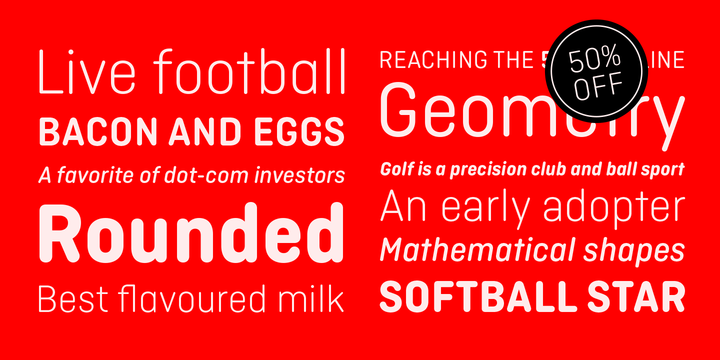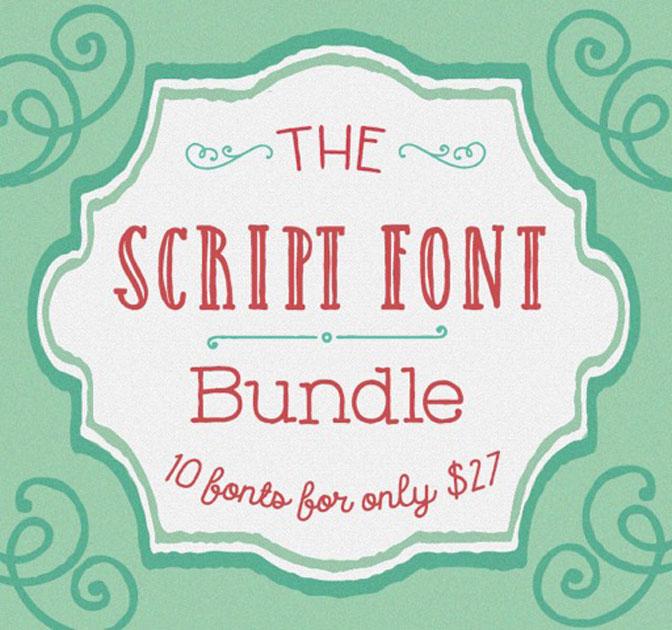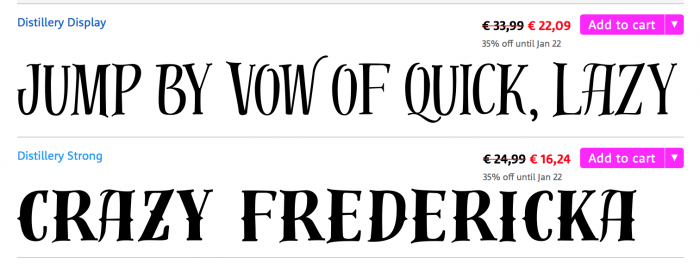
Aber im Ernst: Soll ich noch mal einen»echten« Text zum Vergleich setzen?
Na, Phantasielatein lese ich nun ja schon seit mehreren Jahren ... daran liegt's nicht. Denn auch den Echttext empfinde ich nicht angenehm im Auge. (Das liegt aber nicht an deinem bezaubernden Text – irgendwie sperrt sich die DINSlab meinem Lesefluss entgegen).
Leider fehlen bei mehrere dieser Schriften jegliche Form von Sprachunterstützung, und sind also nur für englisch geeignet. Trotzdem aber für die andere Schriften kein schlechter deal.
Das stimmt, bei Hipsteria und Graceful fehlt sogar das ß, was sie in unseren Breiten leider ziemlich unbrauchbar macht.
Dann mach einen auf kosmopolitischen Pan-DACHler, der generell nur Strasse schreibt. Es soll ja sogar eigentlich gar nicht schweizerische Firmen geben, die derartige Praktiken pflegen. :hammer:  Aber im Ernst, das hier und da fehlende ß hat mich auch gestört.
Dabei haben all diese Fonts das in verbundenen Schreibschriften ziemlich unnütze Ð (Groß-ð)! Da haben wir’s mal wieder: der halben Million Isländischschreibern wird jeder obskure Wunsch erfüllt, aber 90 Millionen Ösi-Deutschländer werden diskriminiert! Wenn das mal kein Fall für PEGI[selbstzensur! :tutor:]
Aber jetzt wirklich im Ernst: die Schriften bieten auch positive Überraschungen. So haben einige sehr schön subtile Diakritika (so wie Handschreiber das oft machen), also nicht so übertrieben auf Unterscheidbarkeit getrimmt wie in zu vielen Fonts. :biglove:
Gerade bei MyFonts entdeckt: Café Brazil von Sofia Mohr
Café Brasil is a font designed to represent coffee, especially for use in packaging, brand titles, logos and menus. Based on the shape of a coffee bean, Café Brasil has delicate details and ligatures that represent the liquid, foam and steam of a good cup of coffee. In March 2014, Café Brasil was chosen to be part of the main exhibition at the “Tipos Latinos 2014”. (Zitat MyFonts)
Und hier noch eine Hübsche von Schizotype: Urge Text
Und zwei der Distillery-Schnitte gefallen mir auch gut:
Da muss ich direkt an die Werke von Tim Burton denken …